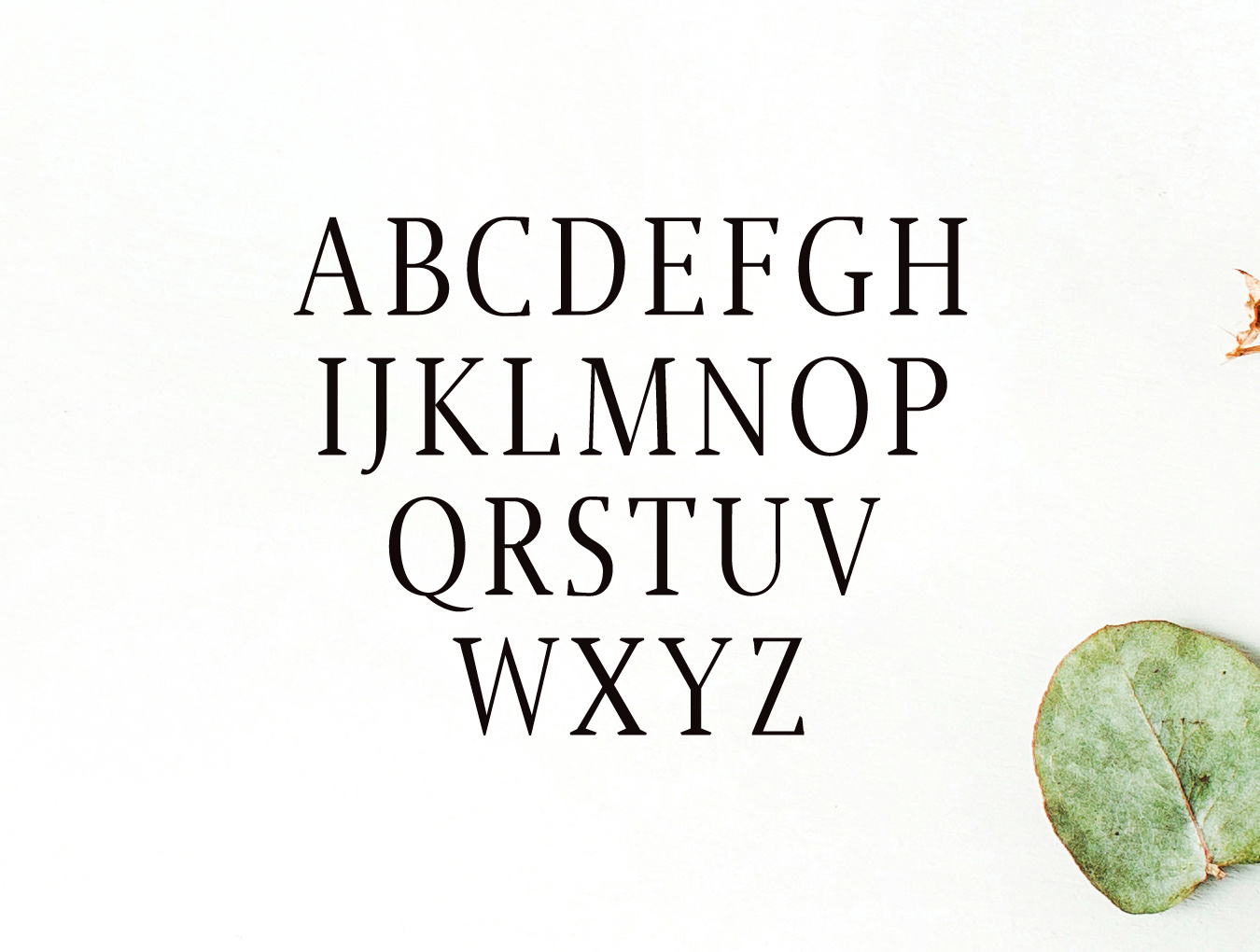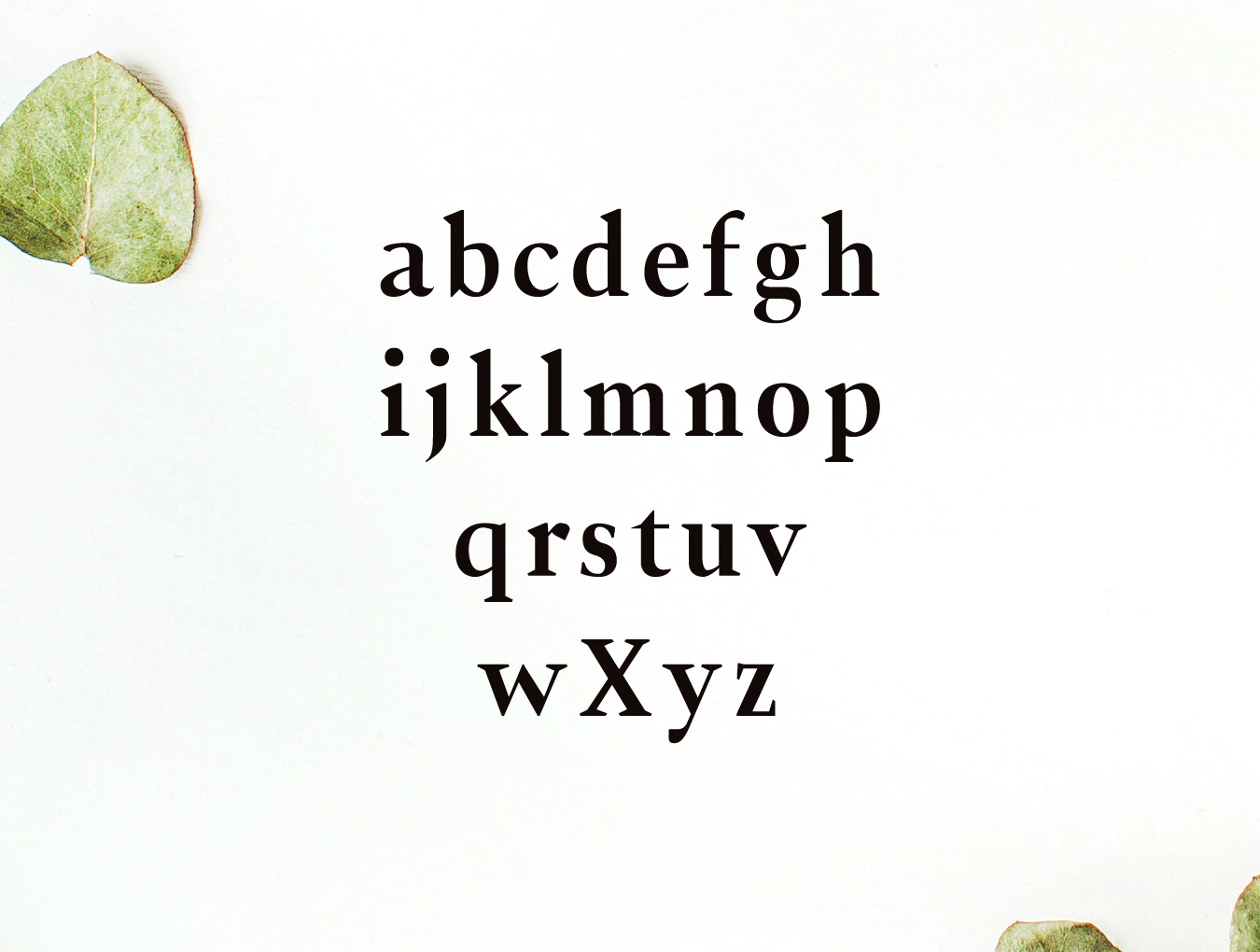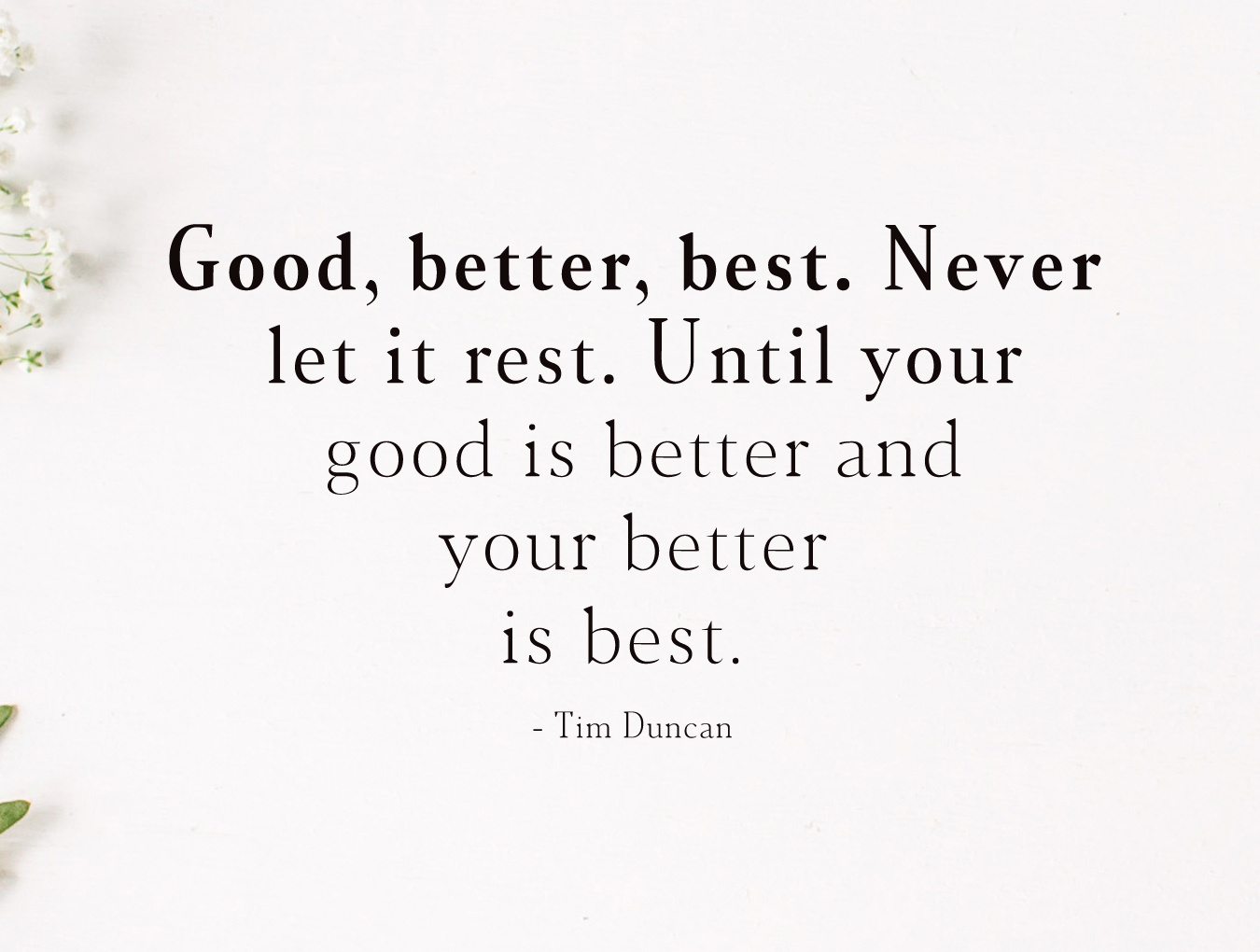
Jerrick Serif 6 Font Pack,Jerrick Serif
Jerrick Serif 6 Font Family Pack具有独特而现代的衬线外观和感觉。非常适合华丽的徽标,标题,网页布局和品牌。如果你想尝试一个优雅的外观,它看起来华丽,所有帽子都有宽大的间距,或者在大写字母和小写字母中完美无瑕。